东亚7家独立字体公司,入选 It s Nice That
字体设计大盘点
来自东亚中日韩三国
近日,It's Nice That发布了一份关于对全球字体领域的100家独立工作室的调查报告。我们将从It's Nice That选出的东亚地区的7家独立字体公司出发, 围绕中文字体设计,认识中国更多的优秀字体设计师/工作室,一起看看吧!
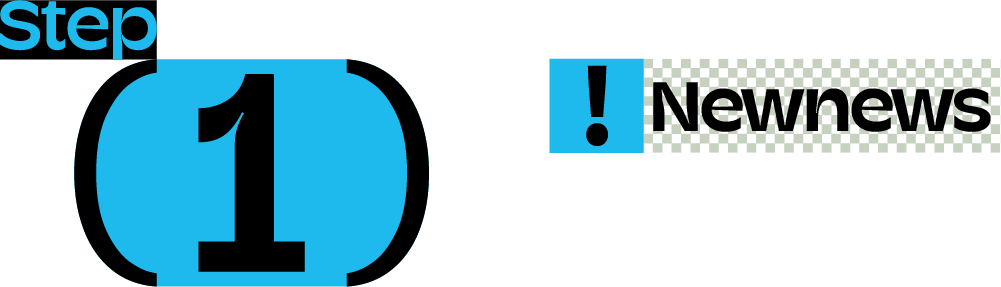
尽管It's Nice That声称这不一定是全球100家“最佳”的独立字体公司,但也是花了很大功夫精心选出的,其中东亚地区只有7家独立字体公司入选,分别是韩国4家,日本2家,中国2家。一起看看!
3type(三言)
入选作品:Memo
入选作品:修竹
火山字型,由一位从业多年的平面设计师创建,每套字体的风格设定皆来自日常设计需求中,2016年开始成体系的制作中文字库,并于2020年正式公开发行三套原创中文字型——眉月、悍石、修竹,如今正在制作第七套原创中文字型“青荷”,坚持独立美学价值观,致力于呈现妙趣、严谨、雅致的中文精作字型产品。
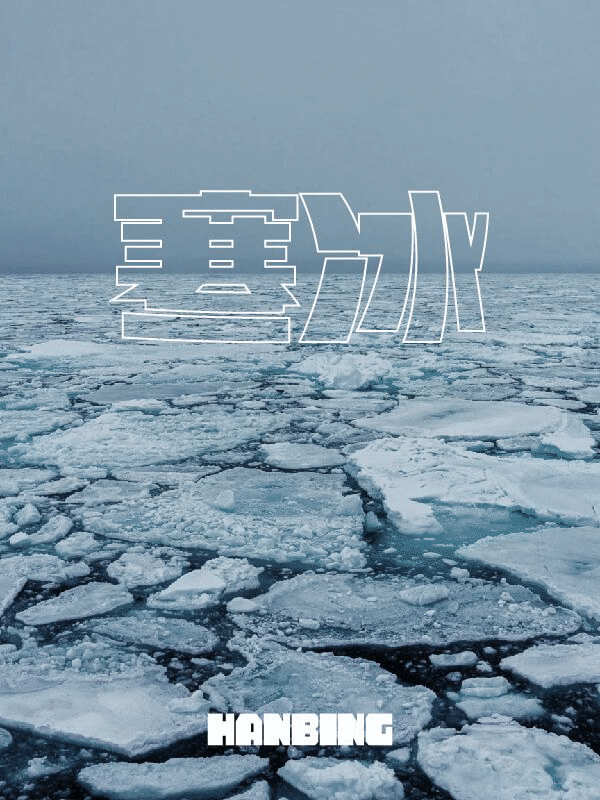
入选作品:修竹
修竹,一款偏向正文阅读性的现代字型,既保留了传统字形的典雅,也流露出现代审美情趣。在局部创新性方面有些新的尝试,如将点画处理成横或竖,所有内中横两端留白等。这款字型各笔画间呼应成趣,规整雅致,还有方体、圆体两种字形选择,风格鲜明,易读性强。
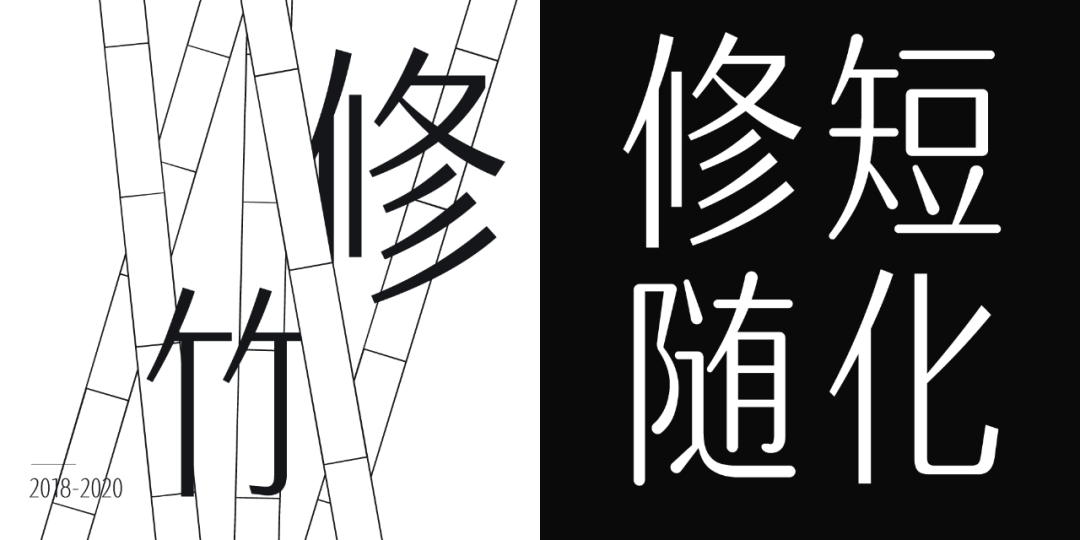
Zin Nagao(永尾仁)
入选作品:ZNVT17
Moolong Type(木龍歩美)
入选作品:Moolong
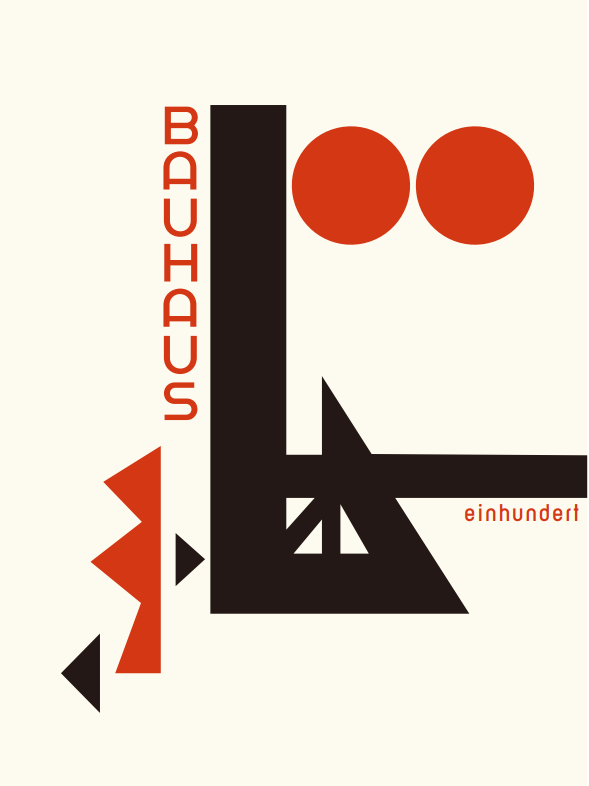
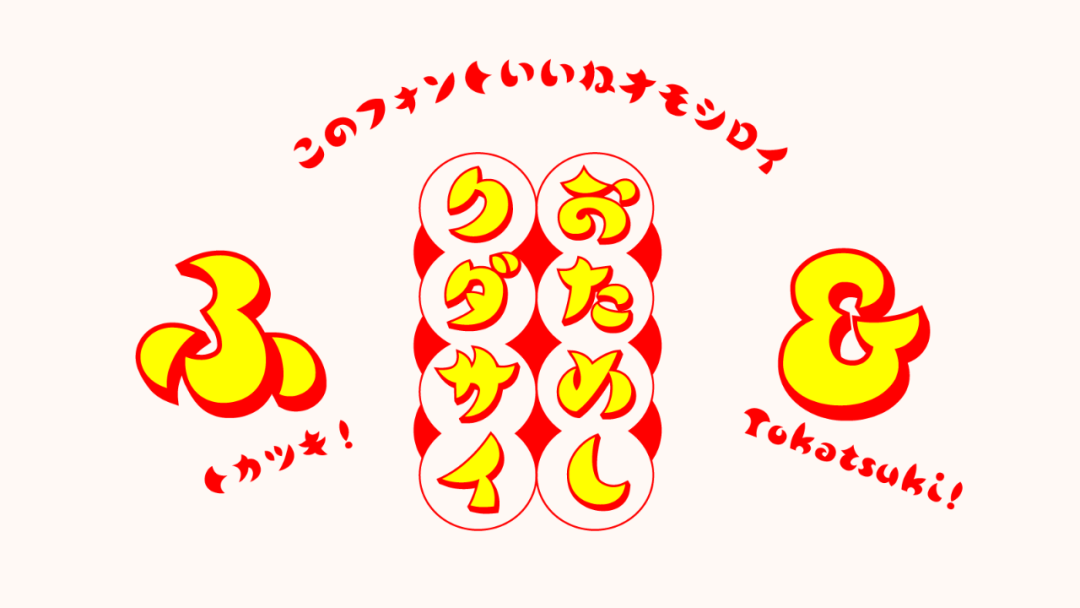
YMG Type Foundry
入选作品:ABC Favorit Hangul
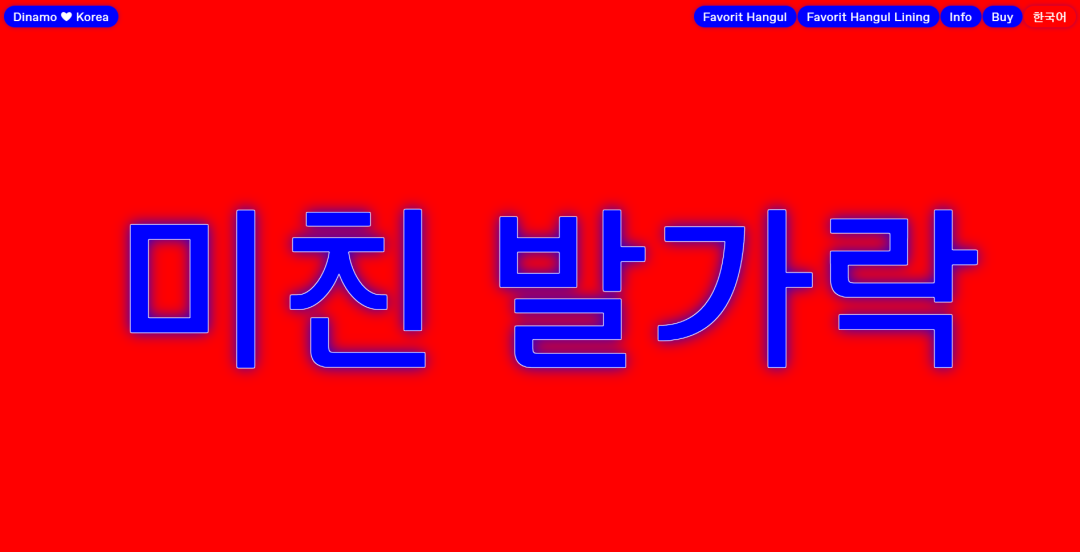
Boomi Park
入选作品:Boomi
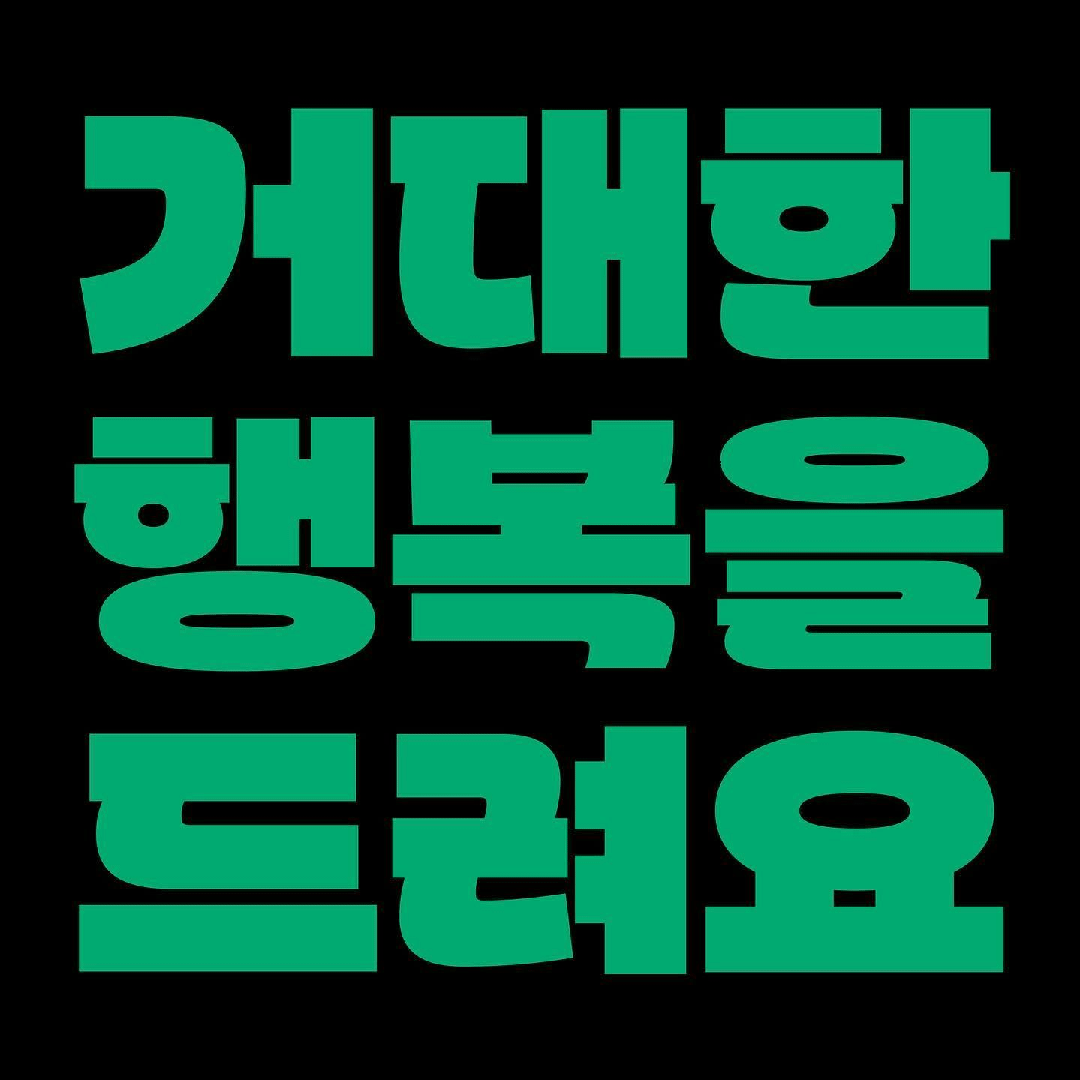
Dong-hoon Han
入选作品:Tlab Psychedelic
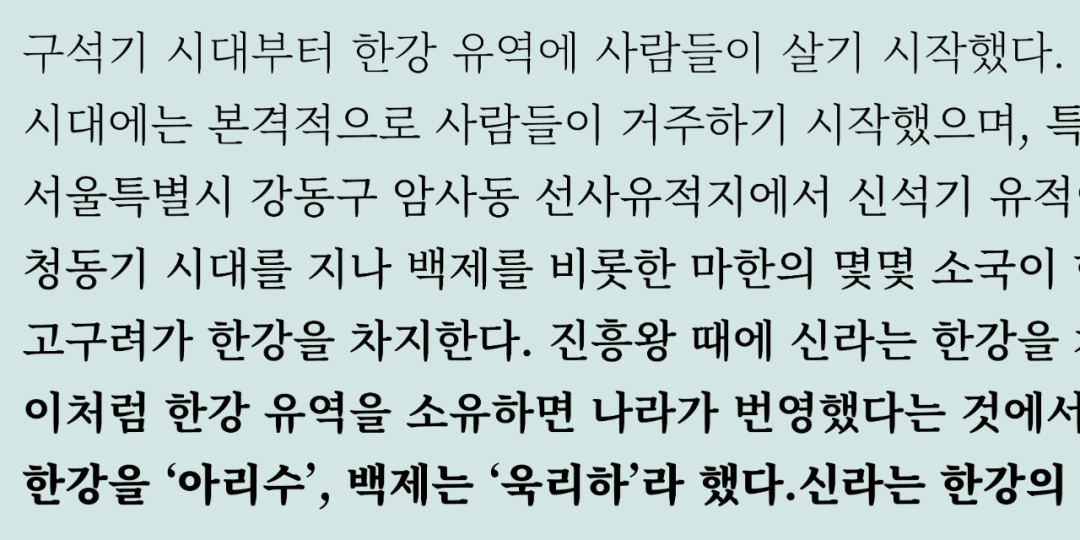
入选作品:Tlab Psychedelic
在It's Nice That调查的这100家全球字体领域的独立设计师/工作室里,仅只有7家来自东亚,其中只有2家来自中国。然而,我们国内优秀的字体设计师/工作室可远不止这些,接下来让我们一起认识一下这5位来自国内的字体设计师吧!
左佐工作室
左佐工作室,是字体设计师左佐成立的个人工作室。正如这个工作室的名字一样,左佐认为这是他正在做的事情的一个招牌,带着安静做事的一种匠气。他通过潜心研究西方和日本的经典著作,结合自己的实践经历,创造出了雨线体、方格黑等字体家族。
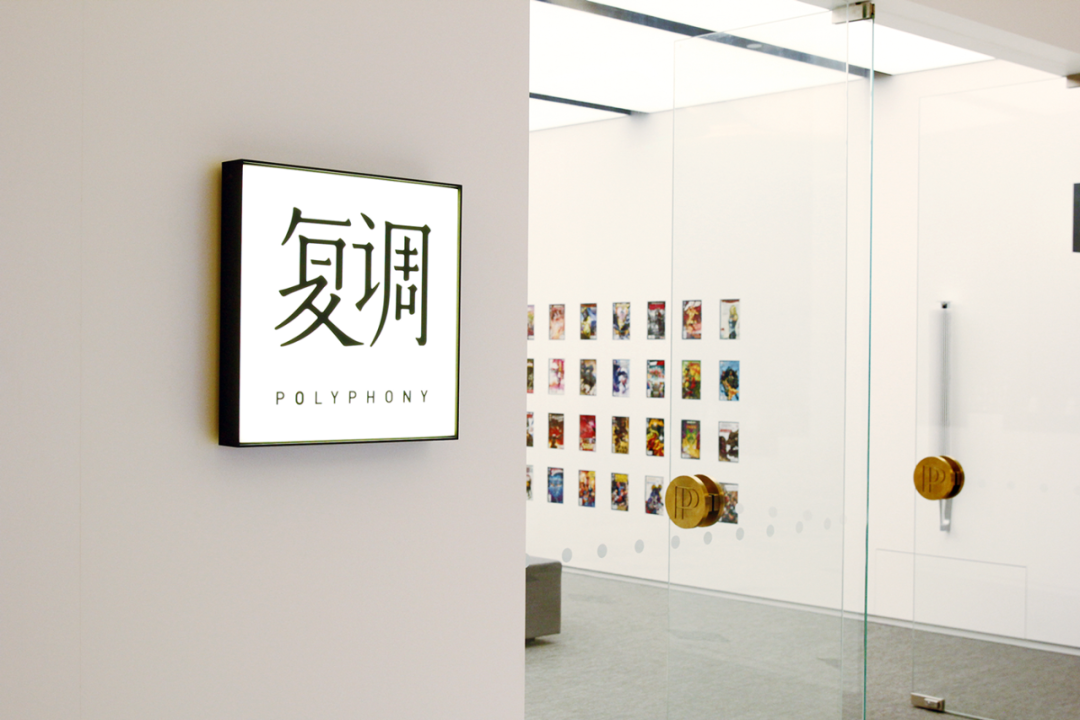
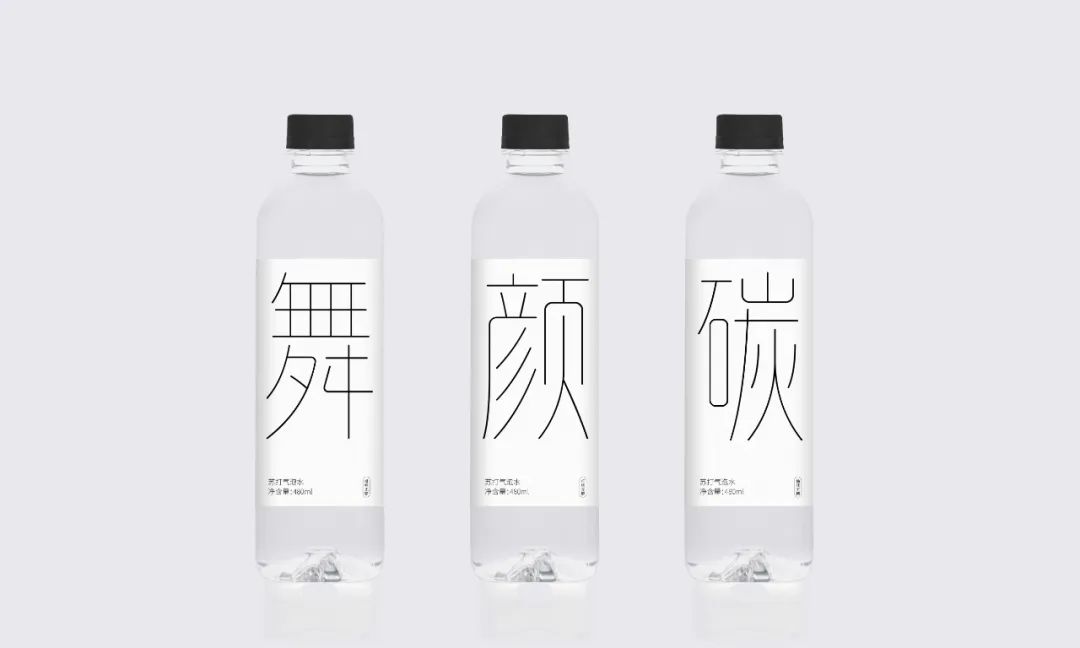
应永会
来自中国宁波的独立字体设计师应永会,在中国传统字体设计上深耕多年,喜爱从古籍善本和民国美术字中汲取灵感,以「字娱字乐」的精神造字,创造出诸多传统风格的字体作品。自2007年以外,他就发表了一系列数字化复刻和汲古字体,其中包括汲古书体、浙江民间书刻体、博州小楷、浙风宋朝体等。
杨林青
杨林青,书籍设计师、出版人。毕业于清华大学美术学院视觉传达设计系,2007年从法国巴黎回到北京成立个人工作室,致力于中国原创出版的策划、编辑和设计,多次获得“中国最美的书”奖等。
周安迪
周安迪,书籍设计师、译者。2018 年在上海创立文化出版品牌“梯”(Telos Books),2020年冬开办了Text&Image梯书店。译著有《设计为何》《怎样用设计改变世界》等。
Adonian Chan(陈濬人)
陈濬人(Adonian) 是少数从事研究和製作的香港中文字体设计师之一,常年走访香港九新界寻访北魏楷书的痕迹,专注于北魏楷书研究,将北魏楷书与现代科技生活相融合。